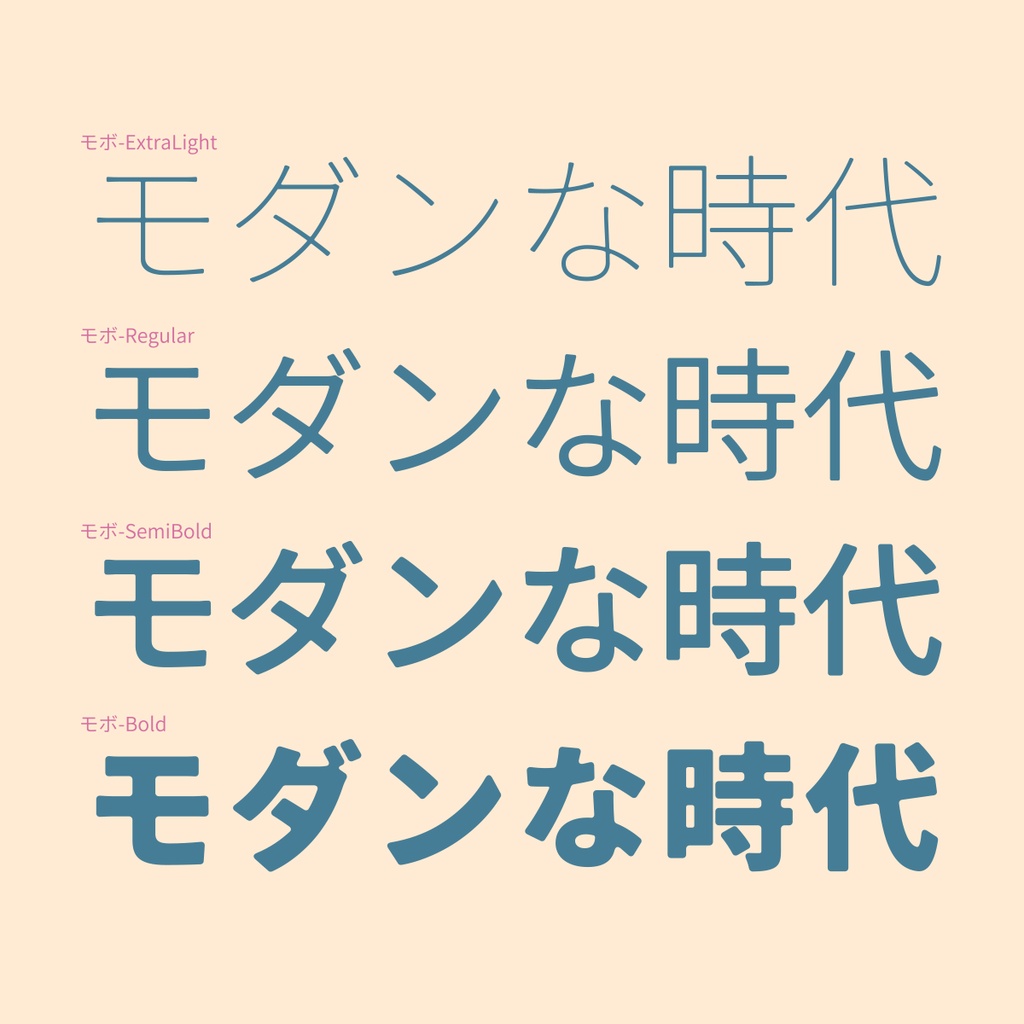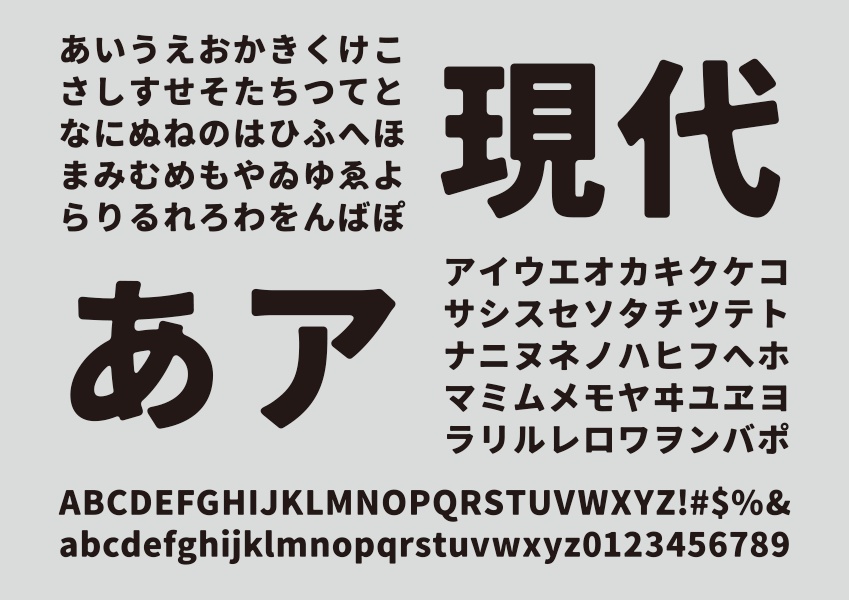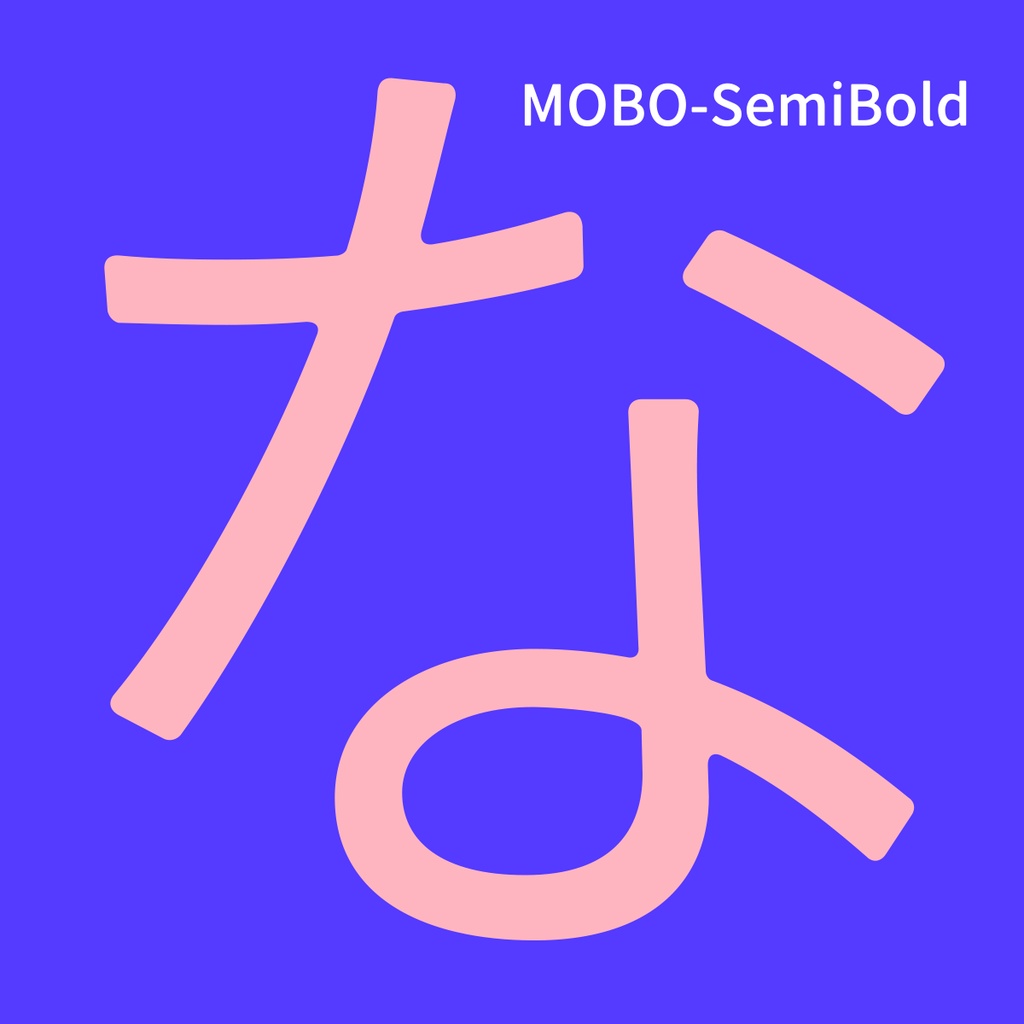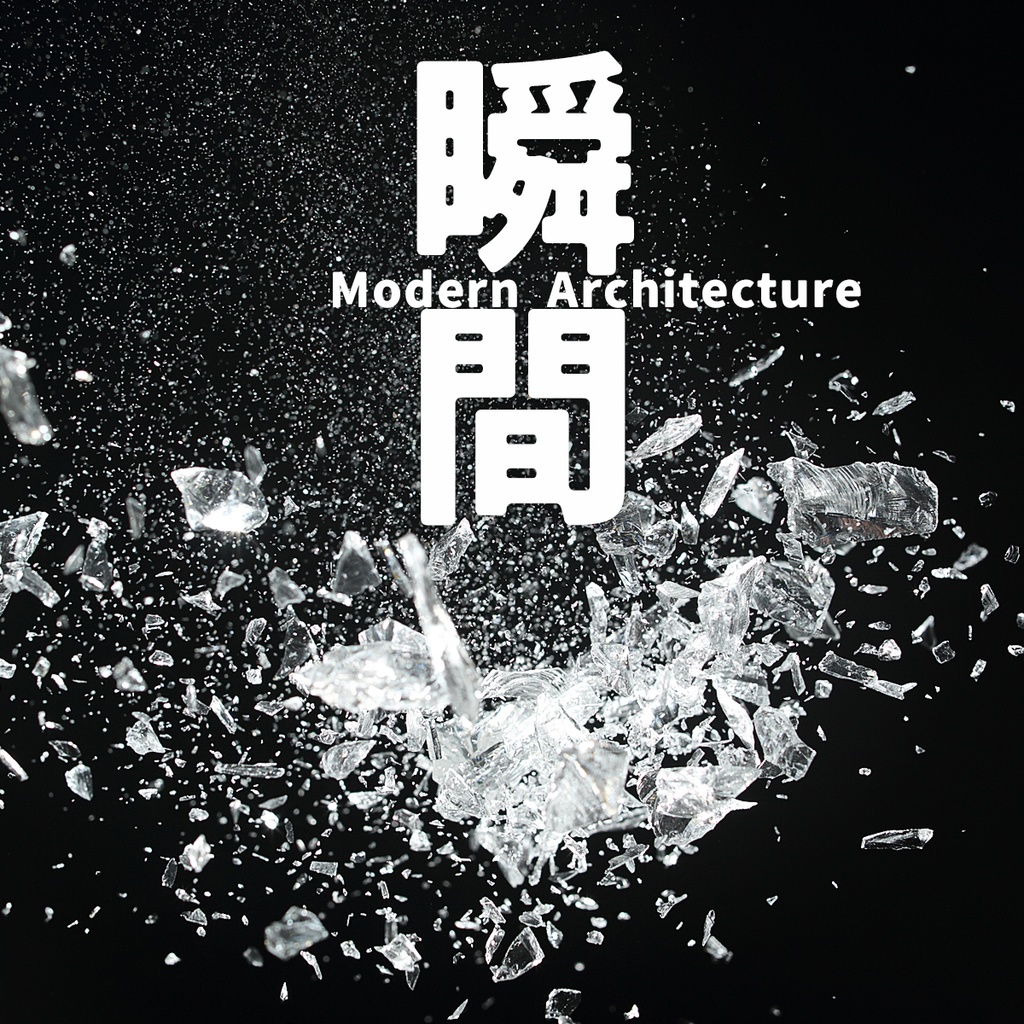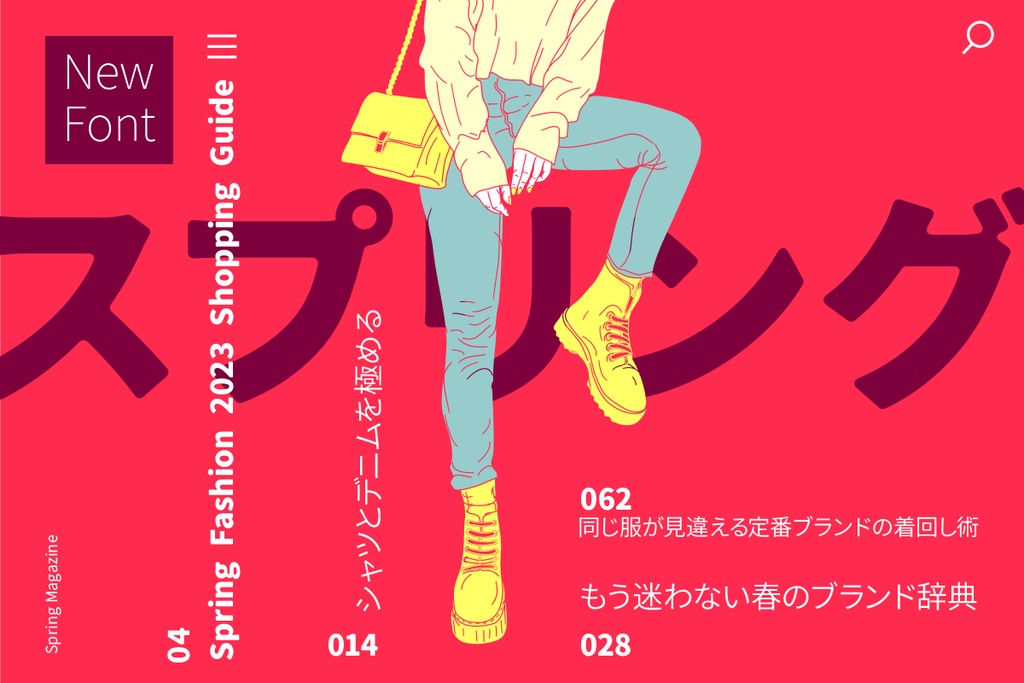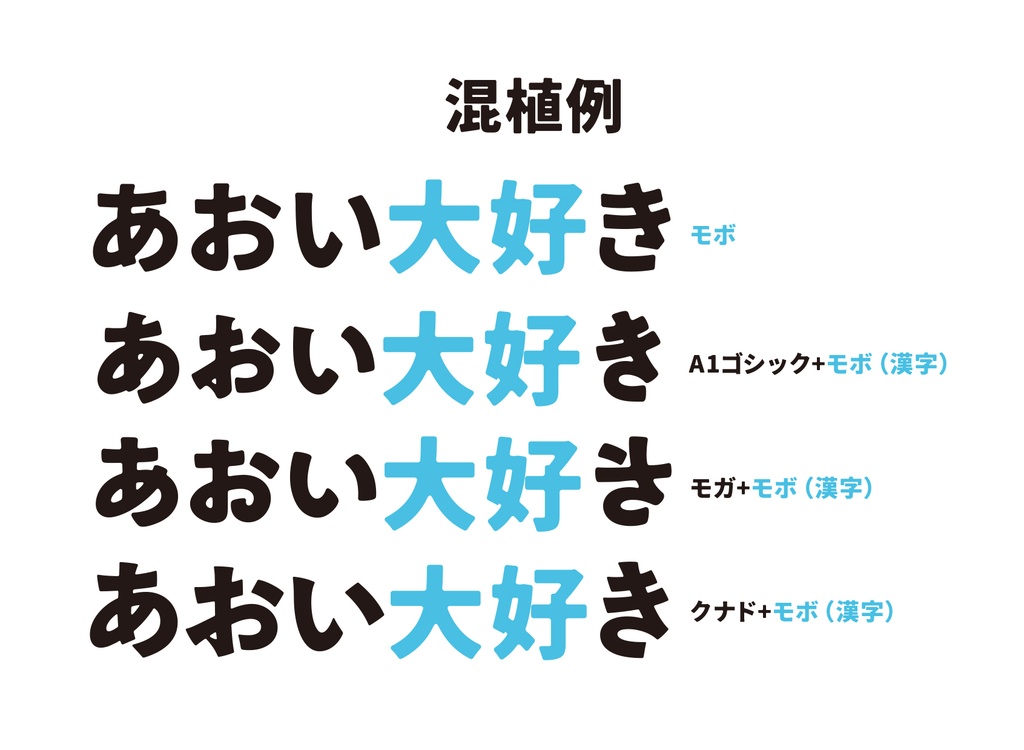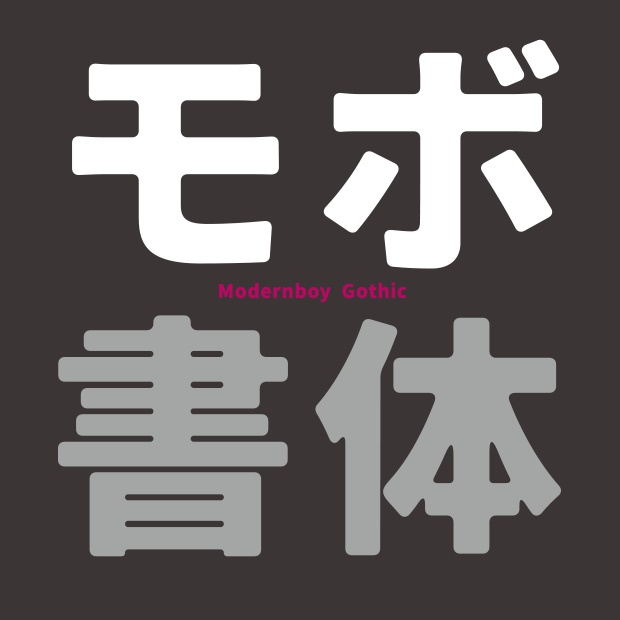
モボ フォントset(Bold、SemiBold、Regular、ExtraLight)
モボは、モダンな骨格の角ゴシックに角丸処理を加えて、やわらかくレトロな雰囲気にしたフォントです。文字数も8000字以上揃っていますので、安心してお使い頂けます。商用利用可能なオープンソースのフォントです。 ■ウェイト Bold、SemiBold、Regular、ExtraLight 太くなるほど角丸の処理が強くなっています。また内側(スミ処理)の角丸は控えめの処理になっています。 人気のモガフォント(https://flopdesign.booth.pm/items/1817411)に合わせる漢字のフリーフォントが欲しいという要望を頂いたので、制作致しました。 ■フリーフォント使用に当たって フォントをインストールして頂くとパソコンのワープロ、グラフィックソフトなどのアプリケーションを使って自由にデザイン、印刷することができます。個人利用・商用利用にかかわらず、無償で使用することができます。当フォントはSIL Open Font License 1.1のオープンソースライセンスに準じます。 ■モボの概要 モボは「源ノ角ゴシック」のフォントを改変して制作した派生フォントです。 制作に関わる全ての方に深くお礼申し上げます。 ⚠️このフォントは自由に動画に使えるフォントです。ご利用の際は次のクレジットを入れていただけると、ものすご〜く喜びます! –––––––––––––––––––––––––––––– フォント:モボ フリーダウンロード:https://flopdesign.booth.pm/items/4647262 –––––––––––––––––––––––––––––– フォローしてください。 Instagram ▶ https://www.instagram.com/flopdesign.font/ X ▶ https://twitter.com/flopdesign